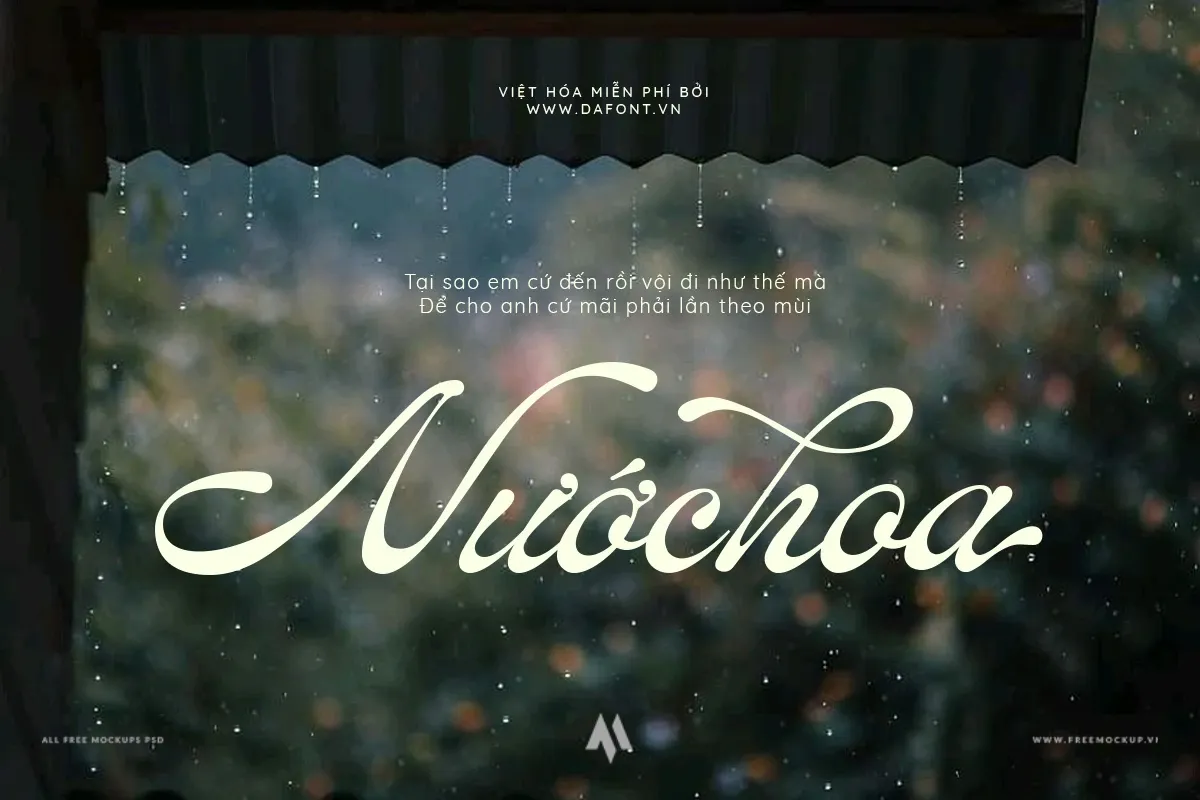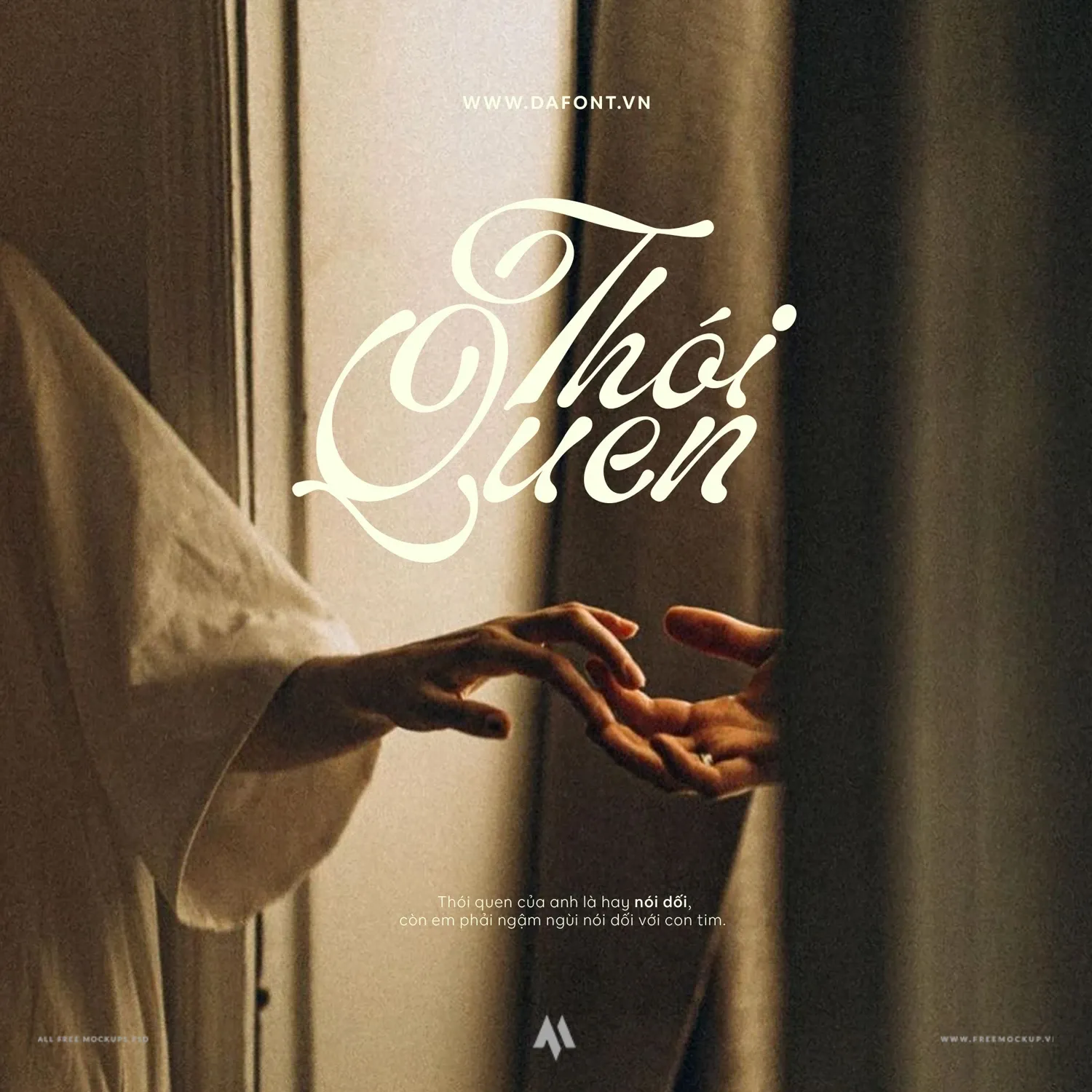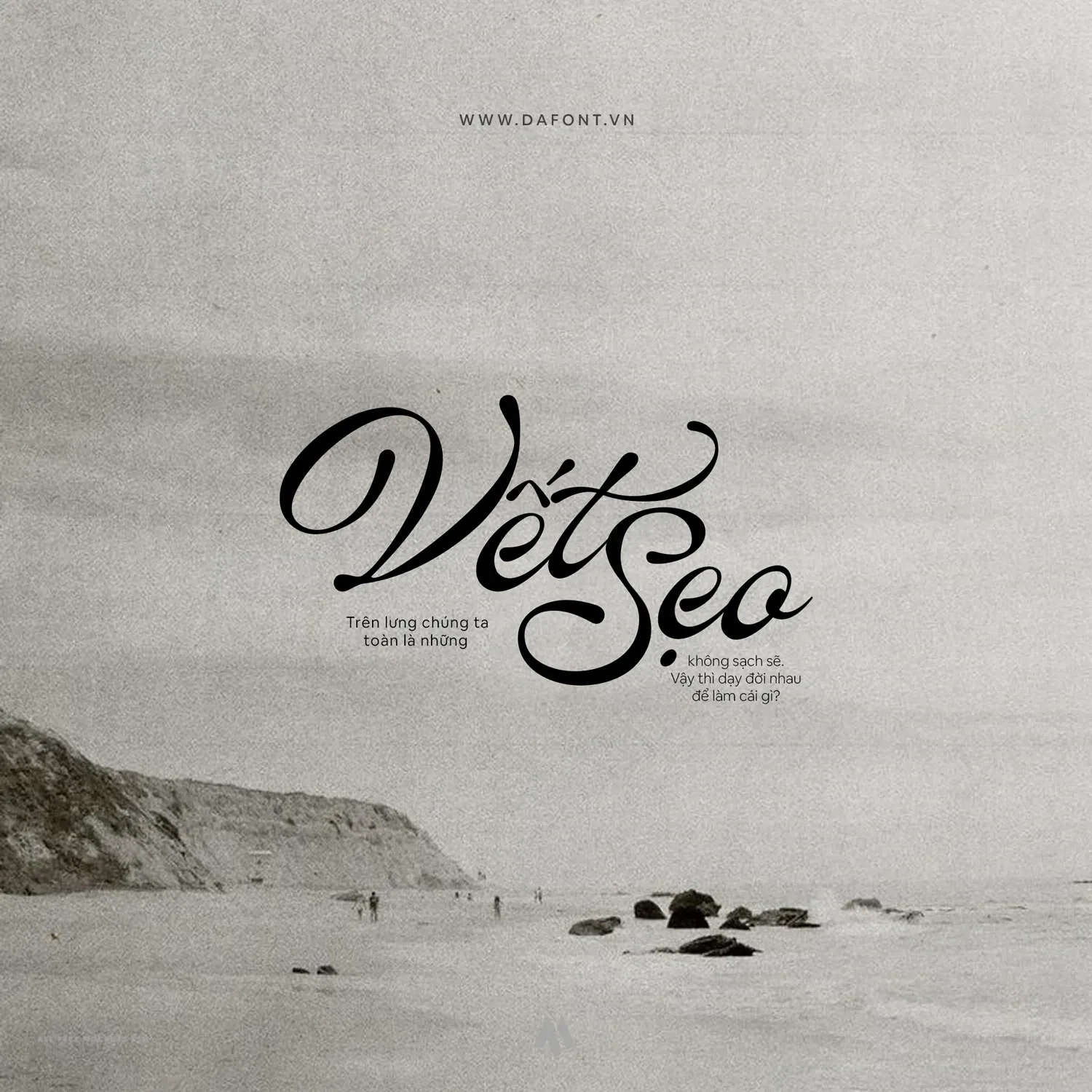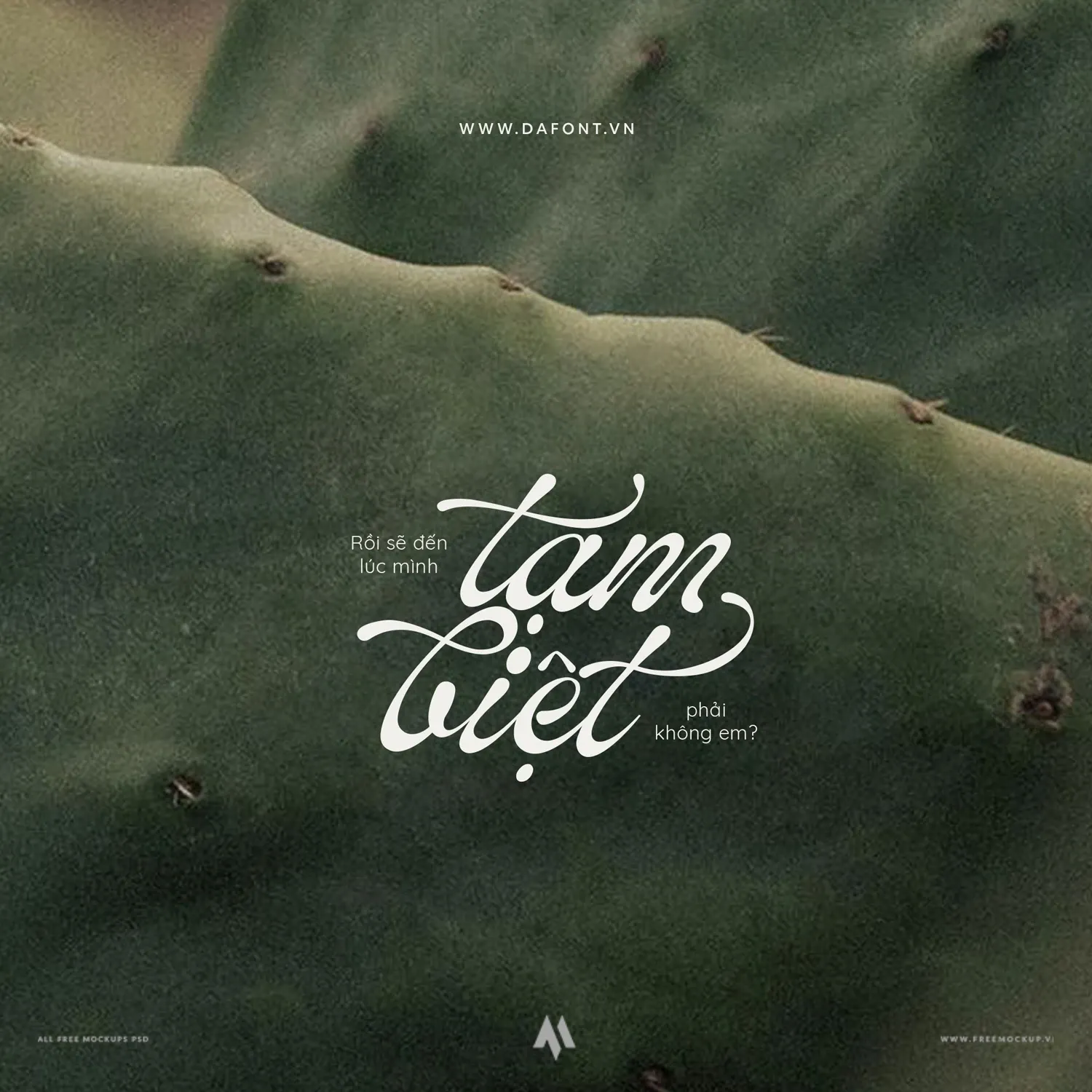
DFVN ED Lavonia Việt Hóa là bộ font chữ viết tay (Script Font) cao cấp được sáng tạo bởi Emyself Design, nổi bật với phong cách cổ điển, quý phái cùng những đường nét uốn lượn mềm mại và thanh lịch. Bộ font mang đến vẻ đẹp sang trọng, tinh tế, giúp các tác phẩm thiết kế trở nên cuốn hút và đậm chất nghệ thuật thủ công.
Đặc điểm nổi bật
- Kho ký tự mở rộng phong phú: Sở hữu hơn 90 Stylistic Sets, Contextual Alternates và Ligatures (nét nối/chữ ghép), cho phép bạn thỏa sức biến hóa và phối hợp các con chữ theo phong cách riêng biệt.
- Việt hóa trọn vẹn và chuẩn xác: Toàn bộ hệ thống dấu tiếng Việt cùng các ký tự thay thế đặc biệt đều được Việt hóa tỉ mỉ, đảm bảo hiển thị hoàn hảo mà không gặp lỗi dấu.
Ứng dụng đa dạng trong thiết kế
- Ấn phẩm sự kiện & Đám cưới: Thiệp cưới sang trọng, thư mời sự kiện cao cấp, thiệp cảm ơn, phong bì quà tặng và menu tiệc.
- Nhận diện thương hiệu: Logo cá nhân, typography nhãn hàng thời trang, mỹ phẩm, spa, thẩm mỹ viện và bao bì sản phẩm cao cấp.
- Xuất bản & In ấn: Tiêu đề bìa sách, tạp chí nghệ thuật, lookbook và poster trưng bày.
- Truyền thông số: Banner quảng cáo, typography nghệ thuật và hình ảnh visual cho các chiến dịch marketing trên mạng xã hội.